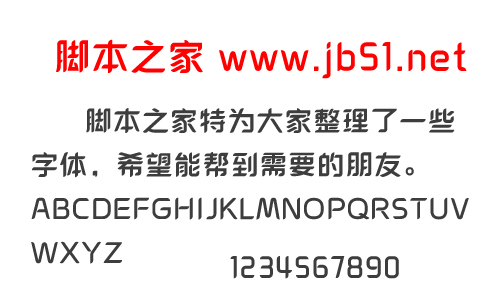
方正本墨悅亦體字體是方正2019年最新開(kāi)發(fā)出的具有現(xiàn)代特點(diǎn)屬性的創(chuàng)意字體,字形結(jié)構(gòu)規(guī)整卻又不失靈動(dòng)可愛(ài)的一面,簡(jiǎn)約、時(shí)尚、優(yōu)雅,具有極強(qiáng)的功能性。適用于導(dǎo)視系統(tǒng)、VI、新媒體等領(lǐng)域。歡迎喜歡方正本墨悅亦體的朋友前來(lái)下載使用。